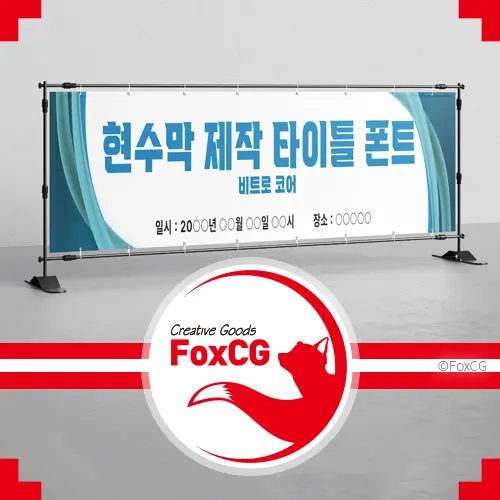
현수막 제작 타이틀 폰트 추천 Best 6 (상업용 무료 폰트)
요즘엔 개인 사업자가 아니더라도 회사나 기관에서도 현수막을 자주 이용하곤 합니다.
특히 연말연시의 각종 행사 시에 행사 제목을 현수막으로 제작하여 부착하는 경우가 많이 있습니다.
막상 디자인 작업을 하려고 하면 어디서부터 어떻게 해야 할지 막막할 때가 많은데 타이틀 폰트만 잘 선택해도 현수막 디자인의 80%는 다 한 셈입니다.
현수막 제작 타이틀 폰트 추천 Best 6 (상업용 무료폰트)
현수막 제작 시 타이틀로 쓰면 좋을만한 폰트 Best 6을 추천합니다.
이 자료만 있다면 누구나 쉽게 원하는 느낌의 서체를 찾아 현수막 시안을 만들 수 있을 것입니다.
현수막 제작 시 타이틀 폰트 고려해야 할 사항
우선 타이틀용으로는 명조체보다는 고딕체가 좋습니다. 가독성이 더 뛰어나기 때문입니다.
그리고 글자 크기 역시 클수록 눈에 잘 띕니다. 다만 지나치게 크면 촌스러워 보일 수 있으니 주의해야 합니다.
또 하나 기억해야 할 점은 자간 간격입니다.
폰트에 따라 다르긴 하지만 일반적으로 -10% 정도 자간을 가지는 것이 좋습니다.
마지막으로 색상 선택인데 배경색과 보색 관계일수록 주목도가 높아진다.
예를 들어 빨간색 바탕 위에 흰색 글씨라면 더욱 강조되어 보입니다.
반대로 파란색 바탕 위에 검은색 글씨일 경우에는 내용을 알아보기 어려워집니다.
먼 거리에서도 한눈에 타이틀이 들어오는 디자인이 좋은 디자인이라 할 수 있습니다.
현수막 타이틀 폰트 추천 Best 6
1. Rix열정도
Rix열정도 폰트
(주)폰트릭스에서 제작한 소상공인을 위한 무료 폰트입니다.
굵직굵직한 선과 역동적인 획이 강렬한 인상을 심어주기 좋습니다.
2. 코트라 볼드체
코트라 볼드체 폰트
대한무역투자진흥공사(KOTRA)에서 저작권에서 자유로운 한글 글꼴을 통해
국민의 편익을 증대하고자 만든 폰트입니다.
진취적이고, 역동적인 폰트로 타이틀로 사용하기에 적당한 폰트 입니다.
3. 검은고딕 (Black Han Sans)
검은고딕(Black Han Sans) 폰트
ZESSTYPE에서 제작한 무료 폰트입니다.
굵고 진한 느낌의 고딕 폰트로 가독성이 우수합니다.
되도록 큰 타이틀에 사용하셔야 가독성을 해치지 않습니다.
4. 이사만루체
이사만루체 폰트
(주)공게임즈에서 2020년 한글날을 맞이하여 만든 무료 폰트입니다.
홍보나 이벤트 등의 대외 활용에 적합하도록 만들어져 타이틀에 유용하게 사용할 수 있습니다.
5. 비트로 코어
비트로 코어 폰트
(주)학산의 스포츠 브랜드 '비트로'에서 2020년 한글날을 기념하여 제작한 폰트입니다.
6. G마켓 산스
G마켓 산스 폰트
쇼핑몰 G마켓의 브랜드 아이덴티티를 담은 무료 폰트입니다.